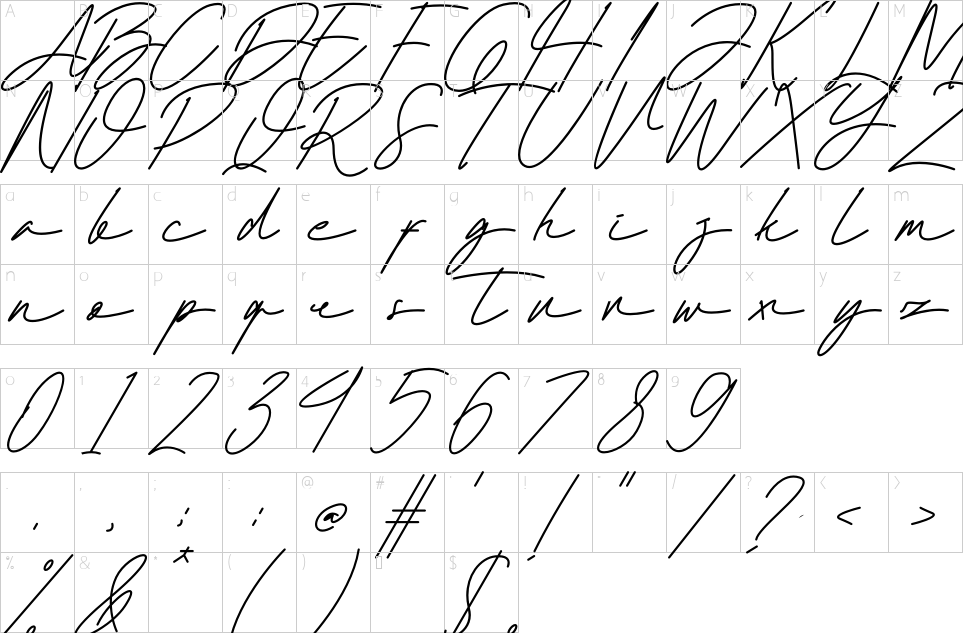
Descubra a elegância do Datonga Font para seus projetos digitais com esta fonte gratuita. Desenvolvida por Jadatype, este belo conjunto de letras é perfeito para designers que buscam uma mistura única e moderna no seu trabalho. Gratuito para todos os sistemas operacionais Windows e Mac, o Datonga é uma escolha inteligente para quem procura qualidade sem comprometer a versatilidade ou o custo. Com mais de 5 mil downloads, você pode estar certo em experimentar a versão da Jadatype deste conjunto de fontes. Seja para criar designs gráficos, blogs pessoais ou até mesmo editoriais online, o Datonga traz uma mistura moderna de linhas elegantes e detalhes sofisticados. Ele é um recurso indispensável para qualquer designer que está em busca de uma fonte clássica mas atualizada. Experimente agora a Datonga Font, uma seleção de letras que certamente se destacará no seu trabalho!